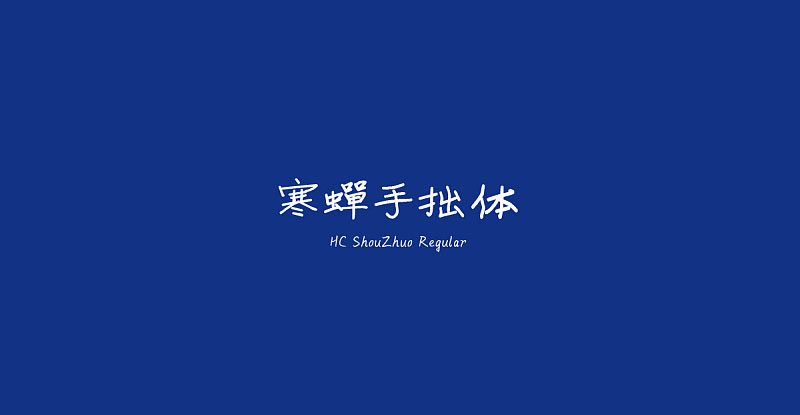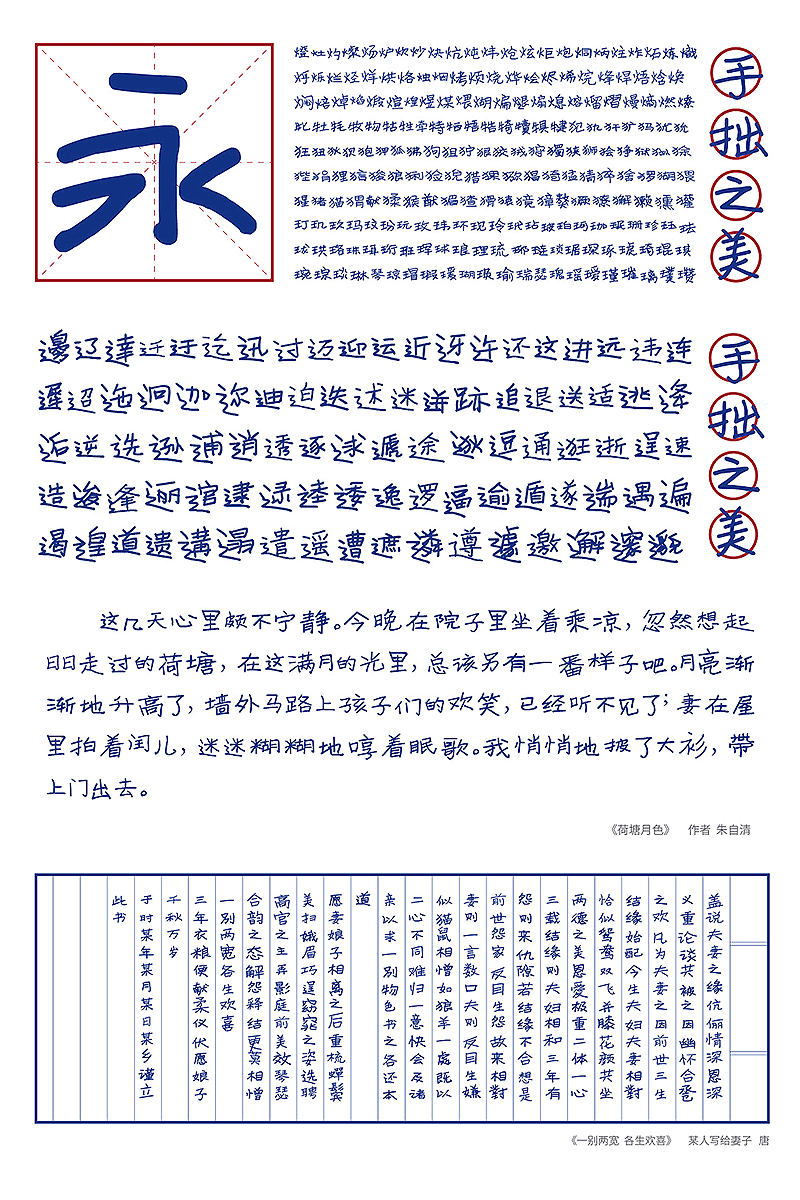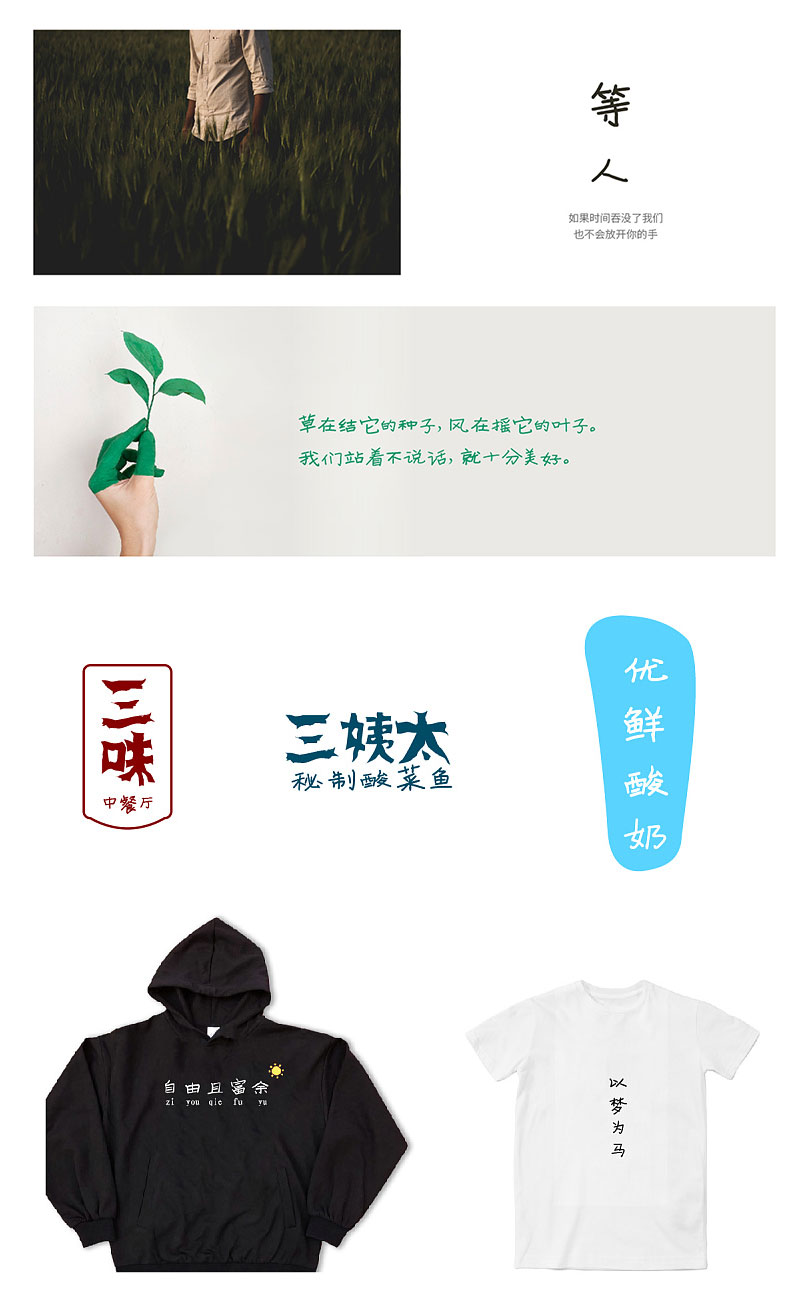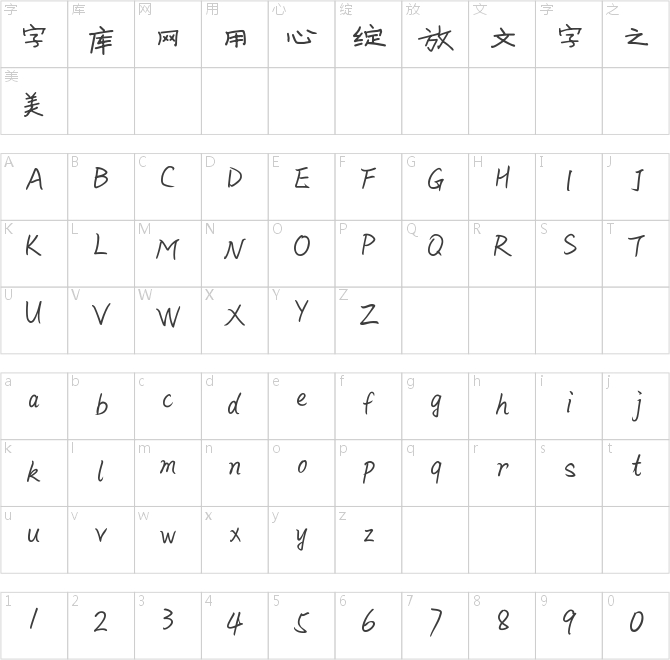
寒蟬手拙體 詳情頁(yè)
寒蟬手拙體是站酷設(shè)計(jì)師 siue 創(chuàng)作的字體,主要精髓為發(fā)掘手寫字體的手拙之美,字體給人一種逼真手寫的視覺(jué)體驗(yàn)。雖應(yīng)用范圍有限,但有其不可替代和獨(dú)特的價(jià)值。以創(chuàng)造的筆意和結(jié)構(gòu)完成,形成風(fēng)格獨(dú)特的一套小眾字體。